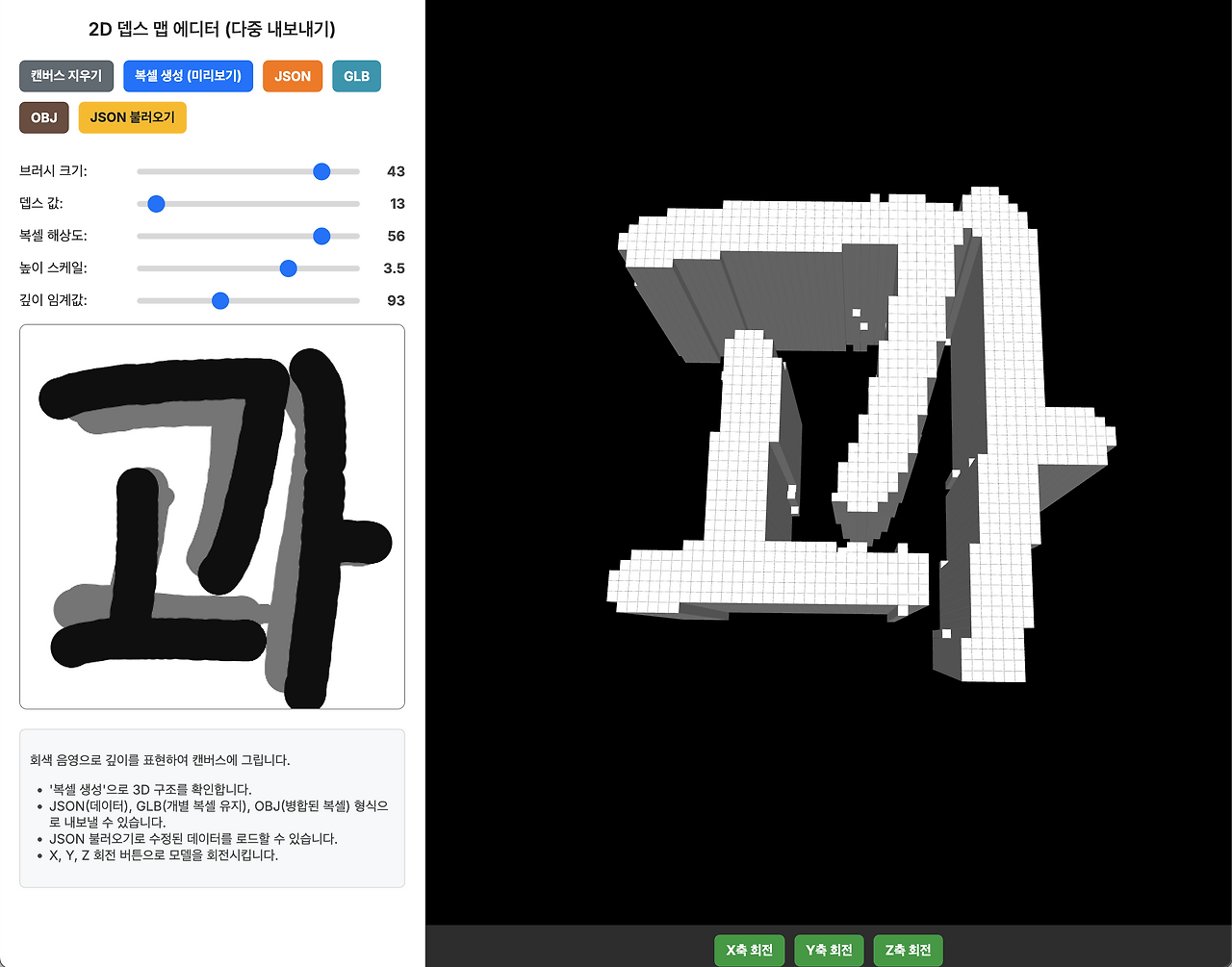
3D로 한글 손글씨 폰트 에디터 만들기
3D 복셀로 한글 손글씨 폰트 에디터 제작 – 05:40
3D Voxel 복셀에디터도 만들고 3D에디터도 만들고 머리가 깨질거 같습니다.
작년부터 진행하던게 손글씨 폰트 만드는 프로그램인데 같은 선을 똑바로 못쓰는 사람들에 대한 여러가지 생각을 하다가 선의 각도가 계속 바뀌는데 이 것을 어떻게 처리해야 할까 하는 고민이 있어서 진행하던 손글씨 부분에 대해서는 두가지 부분에서 마무리가 어렵다 생각했습니다.
일단 내 글씨는 맞지만 비슷하지만 아니다 라는 평가와 수 많은 획에서의 특징을 특정 각도로 맞춰야 폰트로서의 가치가 있는데 손글씨로서는 들쭉날쭉해야 글씨가 사람이 쓴거 같다는 딜레마에 빠집니다.
일단 획을 분리하고 가상의 공간에서 약간의 변형이 가능한 방식을 찾고 거기에 맞추는 방법을 찾기 시작했습니다. 물론 다른 일도 있어서 폰트에는 관심이 멀어졌고...
지난주에 잠시 정리해봤습니다. 뭐 pixel 같은 3D인 Voxel 로 표현했지만 그냥 3D 로 처리하는 에디터로 작성중입니다. 일단 데이터를 확인하는 것중에 하나가 되고 모든 획수를 2D로 그려 놓으면 각도에 따른 조합이 나오는 방식으로 구성합니다.
일단 가능성은 확인했고 앞으로 시간날 때 마무리할 예정입니다.